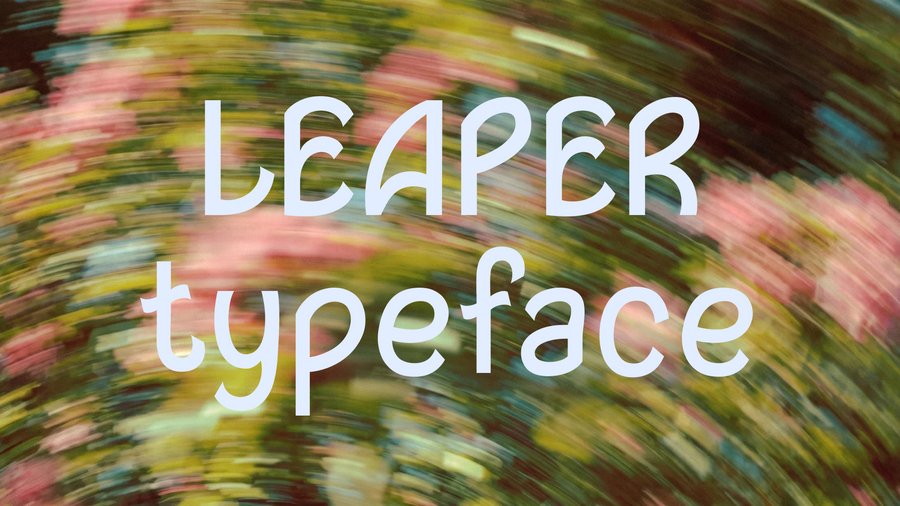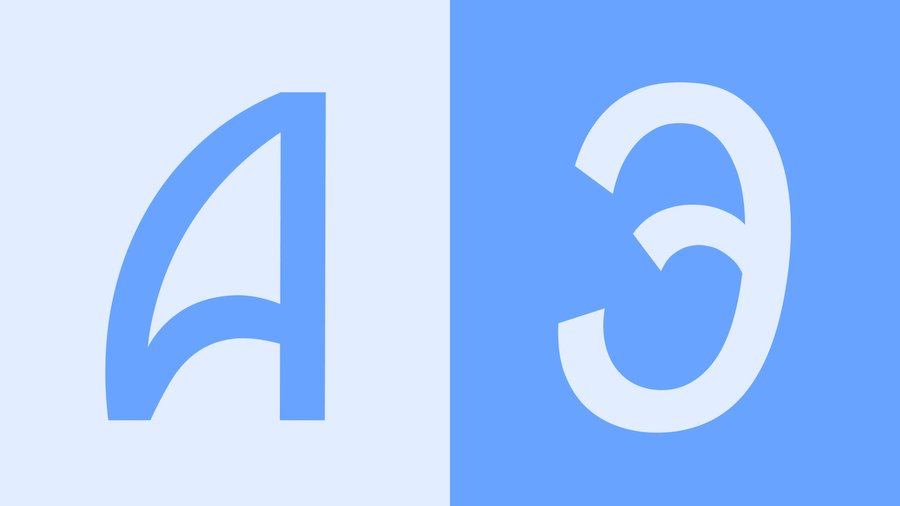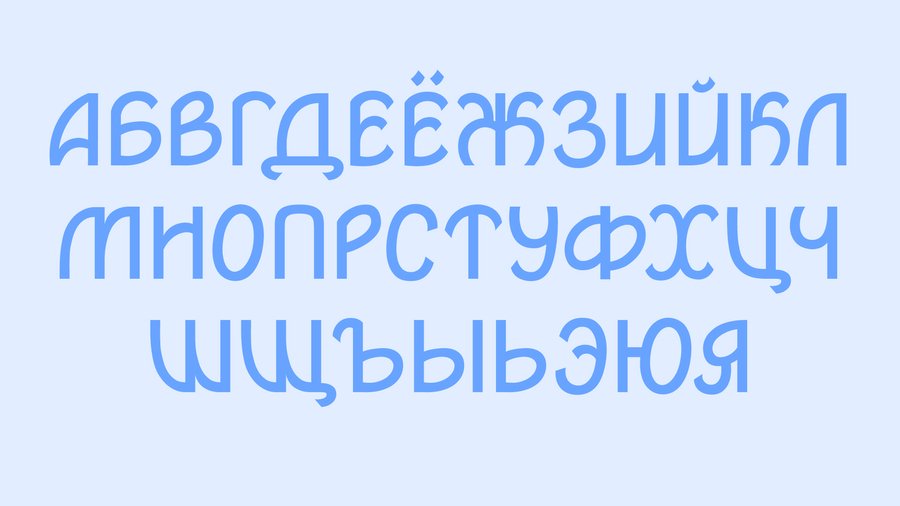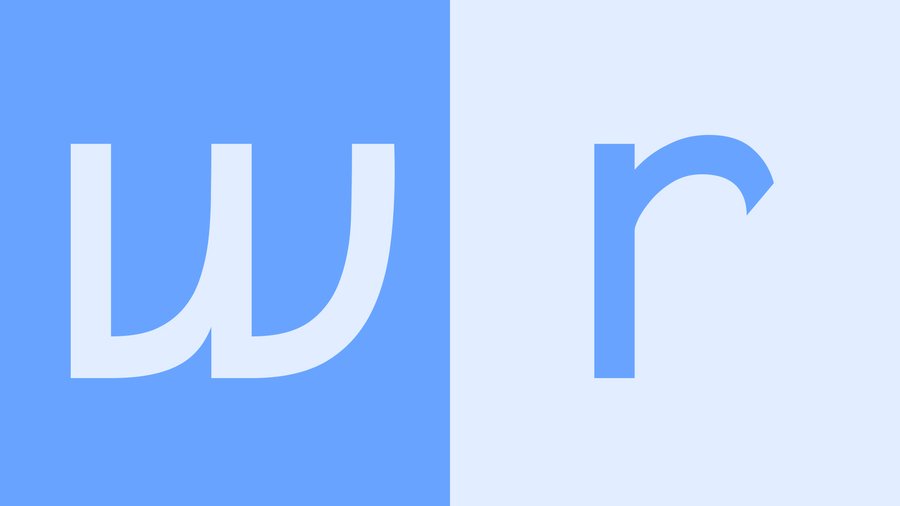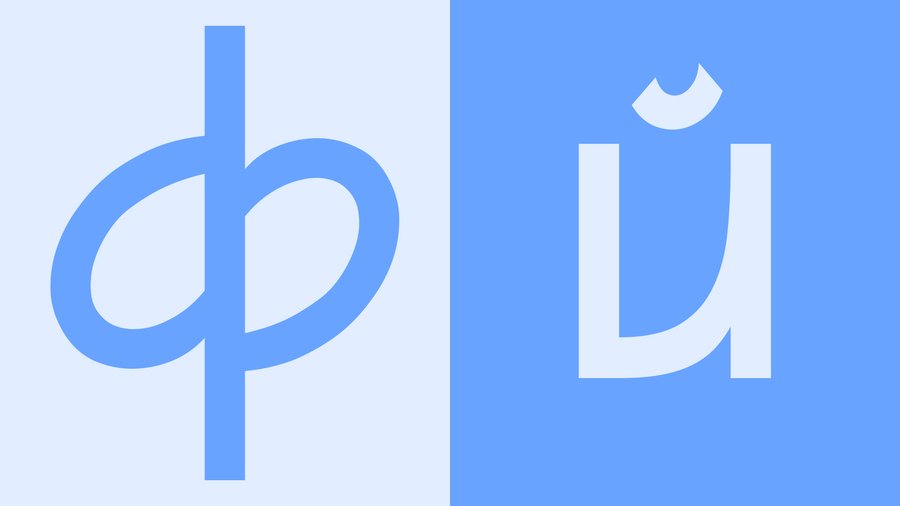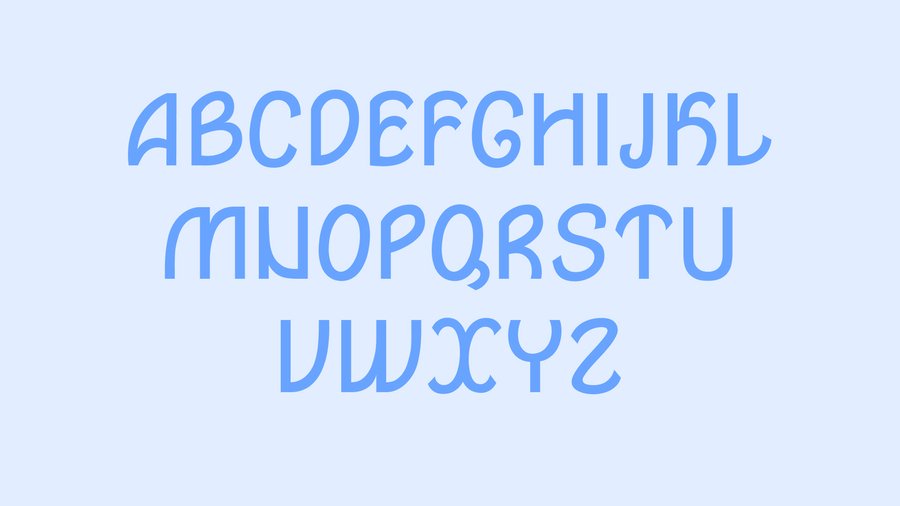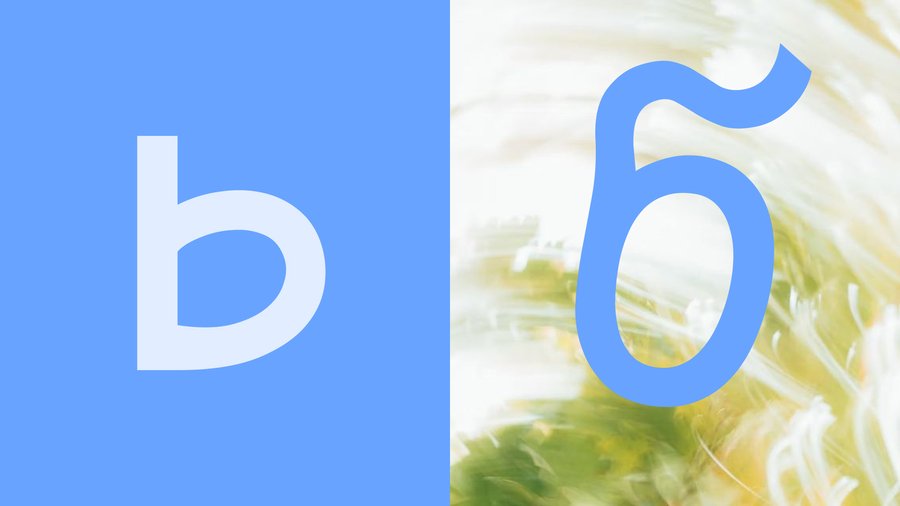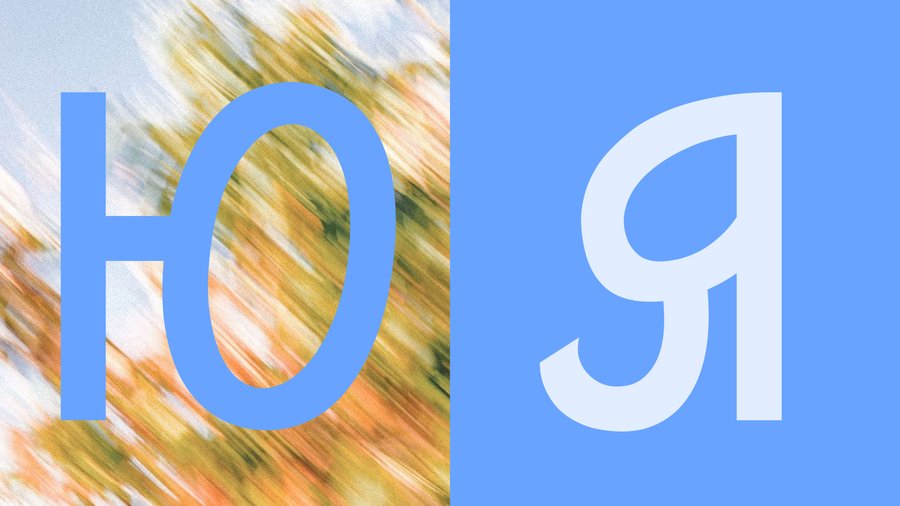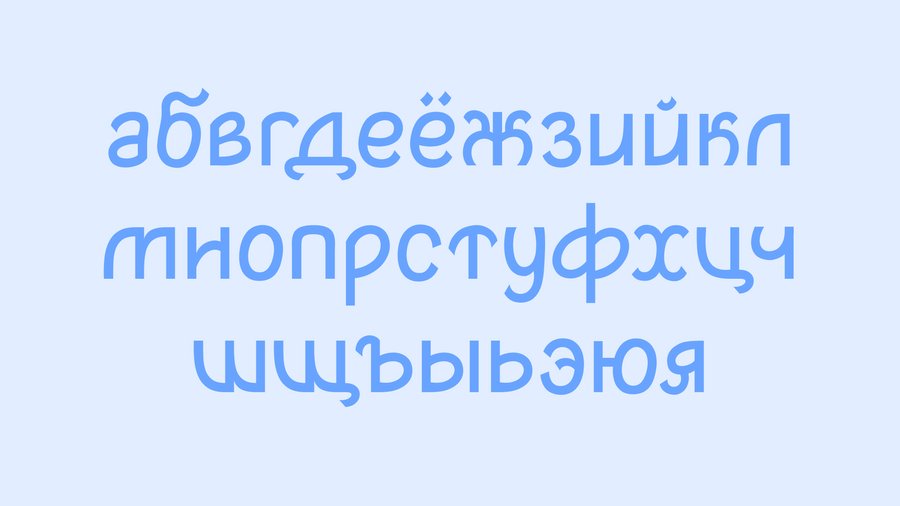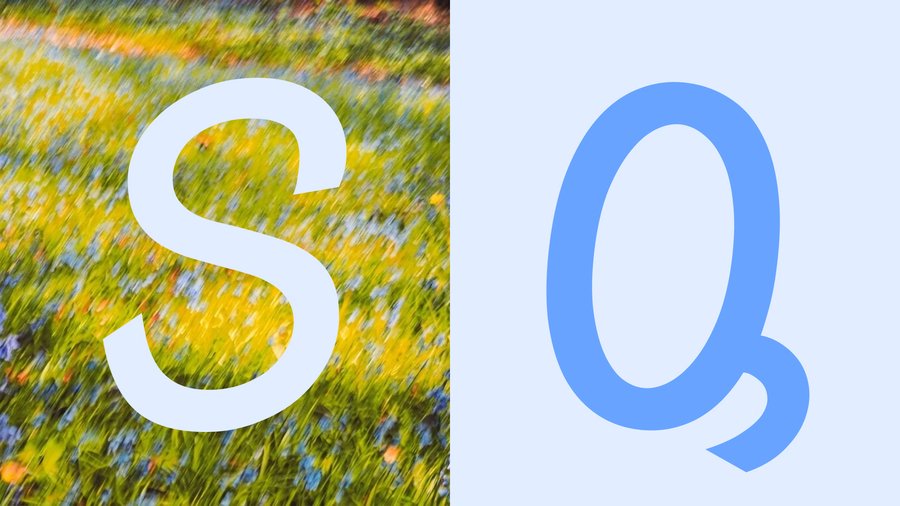
LEAPER TYPEFACE
LEAPER — динамичный гротеск с наклонными круглыми элементами и изогнутыми штрихами. Высокая средняя линия делает его дружелюбным, а заостренные терминалы добавляют непредсказуемости. Иногда он немного несуразный, но зато движется только вперед!
В ходе работы появилась ассоциация с прыжком, отсюда появилось название гарнитуры (leaper — «прыгун» в переводе с англ.)
Помимо наклонных элементов, у шрифта есть еще несколько особенностей — у неокруглых букв обязательно должен быть прямой стем, а у букв с основной массой в левой стороне допускается его подъем.
латиница
Диакритические знаки повторяют динамику штрихов, а в некоторых знаках допускается симметрия и низкая средняя линия.
кириллица
цифры и специальные символы